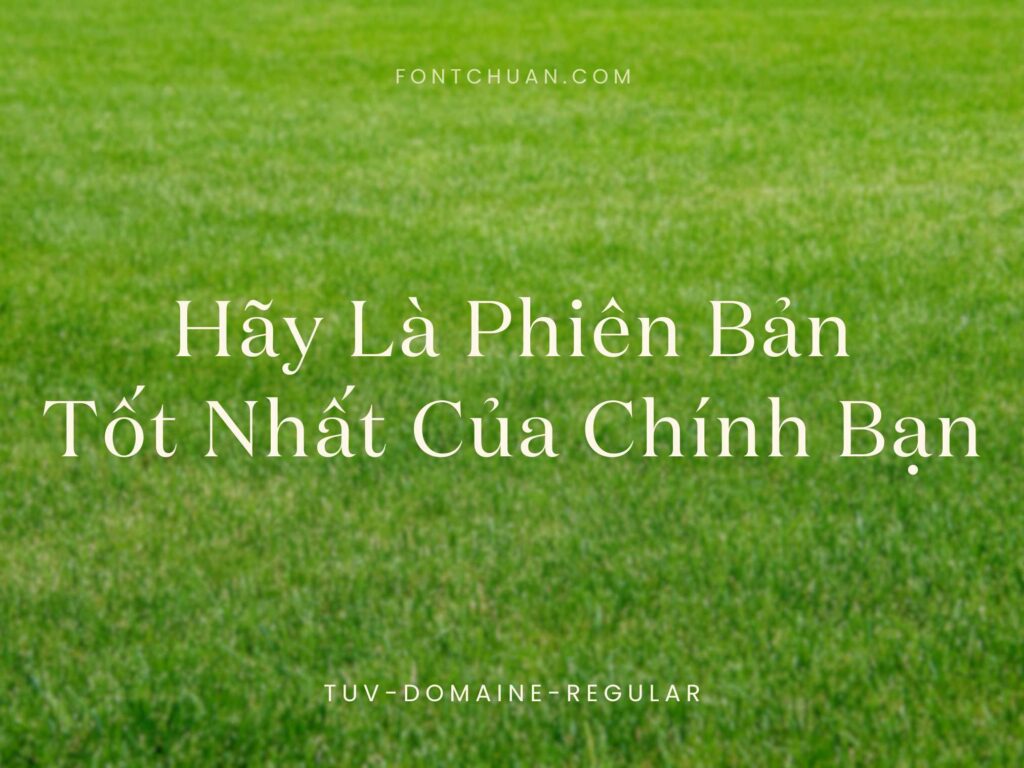
Font TUV Domaine Regular Việt Hóa
Domaine là một font chữ serif sắc nét và thanh lịch, được thiết kế bởi Kris Sowersby và phát hành bởi Klim Type Foundry. Font này kết hợp giữa phong cách truyền thống Pháp và Anh, tạo nên một thẩm mỹ đương đại. Với các chi tiết Latin cong và chân chữ hình tam giác nhẹ nhàng, Domaine mang lại cảm giác tinh tế và hiện đại. Font đã được Việt hóa để hỗ trợ tiếng Việt bởi Thùy Uyên, giúp người dùng Việt Nam dễ dàng áp dụng trong các dự án thiết kế. Font này được sưu tầm và chia sẻ bởi thành viên của Font Chuẩn, đáp ứng nhu cầu sử dụng đa dạng trong cộng đồng thiết kế.
Đặc điểm thiết kế của Domaine bao gồm các chi tiết cong và chân chữ hình tam giác nhẹ nhàng, tạo cảm giác tinh tế và hiện đại. Font này phù hợp cho các ứng dụng như thiết kế tiêu đề, logo, bố cục tạp chí và các dự án sáng tạo khác. Các ngành nghề phù hợp bao gồm quảng cáo, giáo dục và công nghệ.